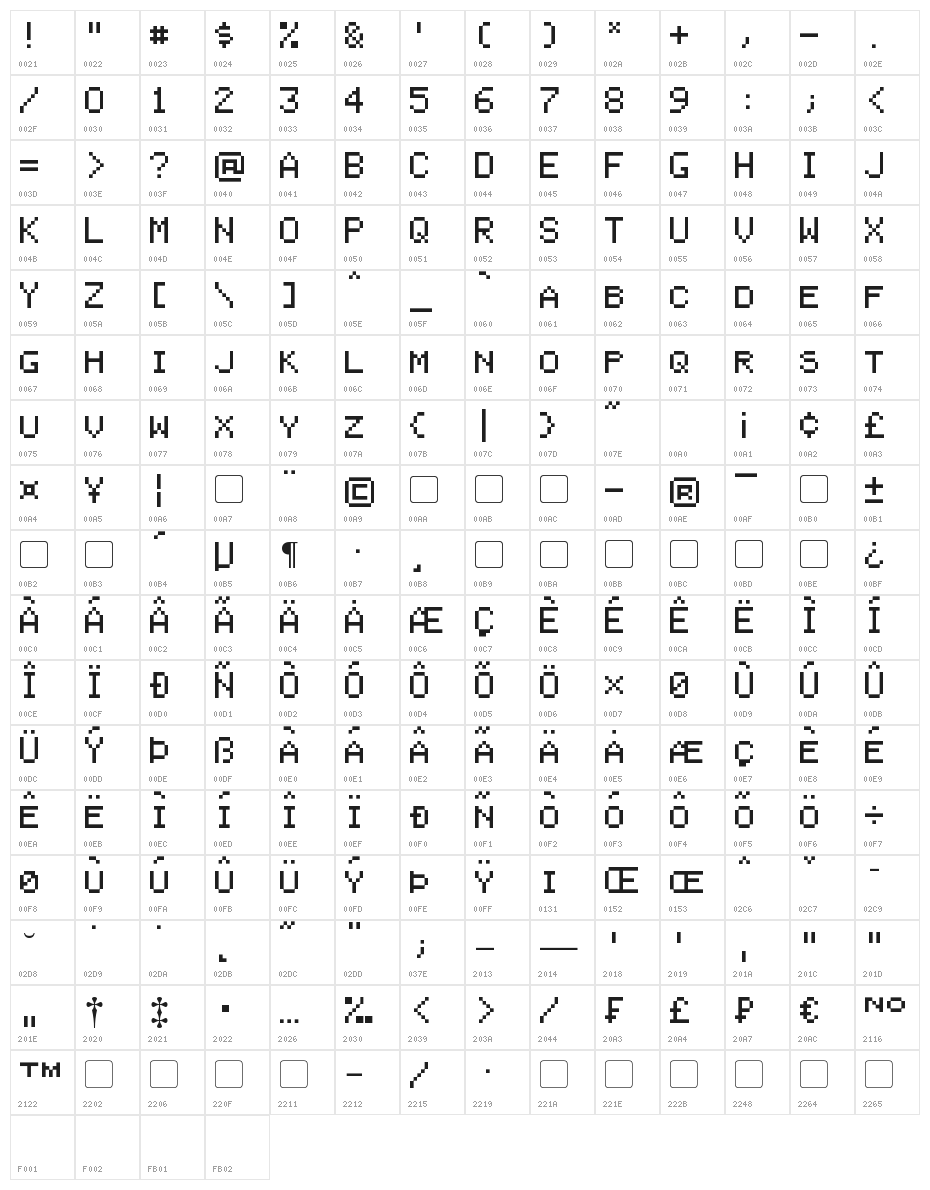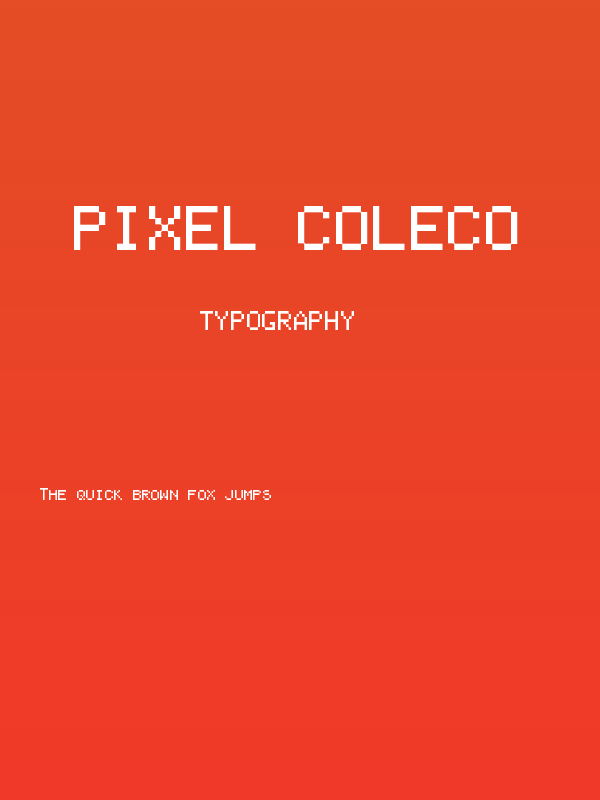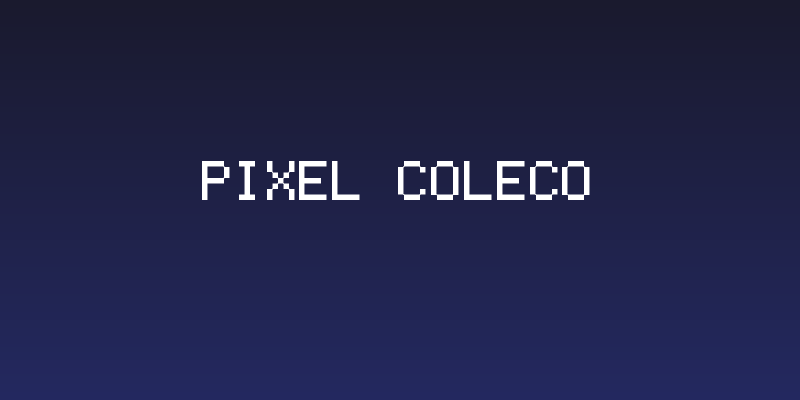
Pixel Coleco Font
| Estilo general | Retro, Digital |
| Caso de uso | Headlines, Logos, Digital Art |
| Proyectos propuestos | Ideal for retro video game designs, digital art projects, and any creative work seeking a nostalgic, 8-bit aesthetic. |